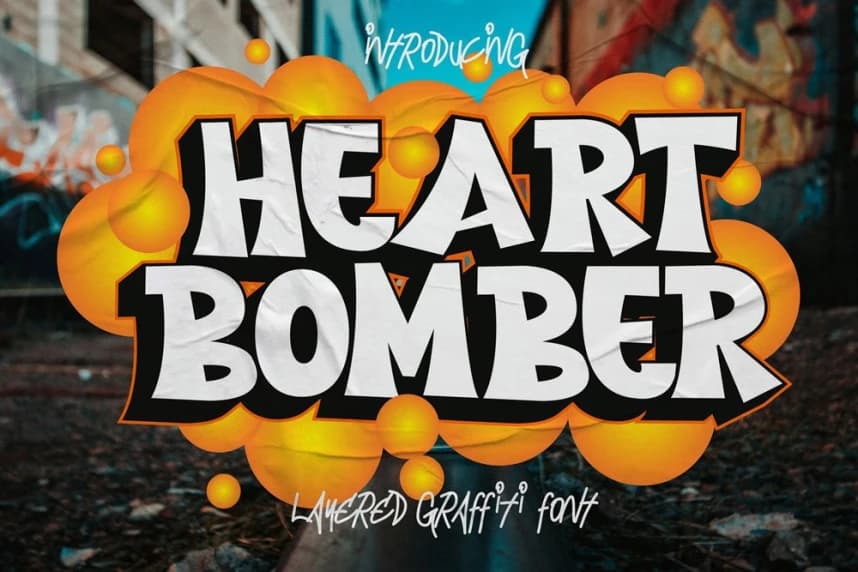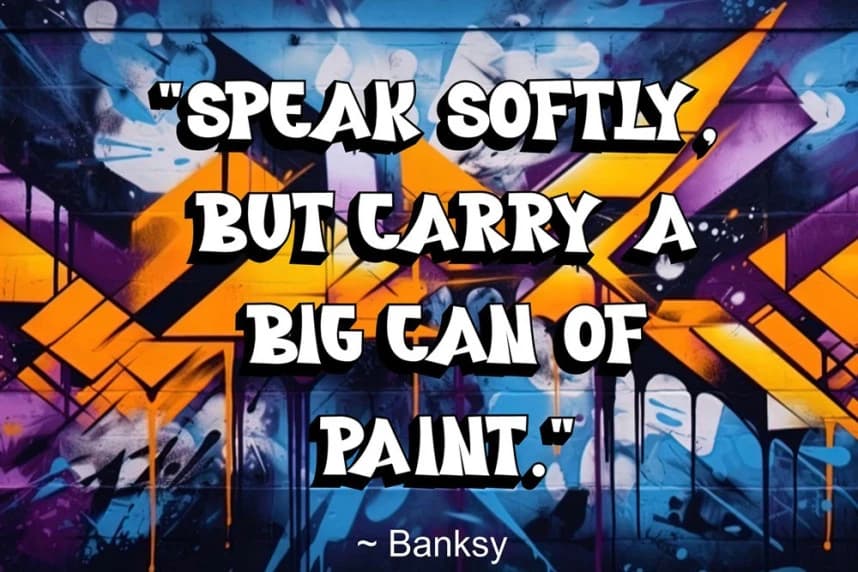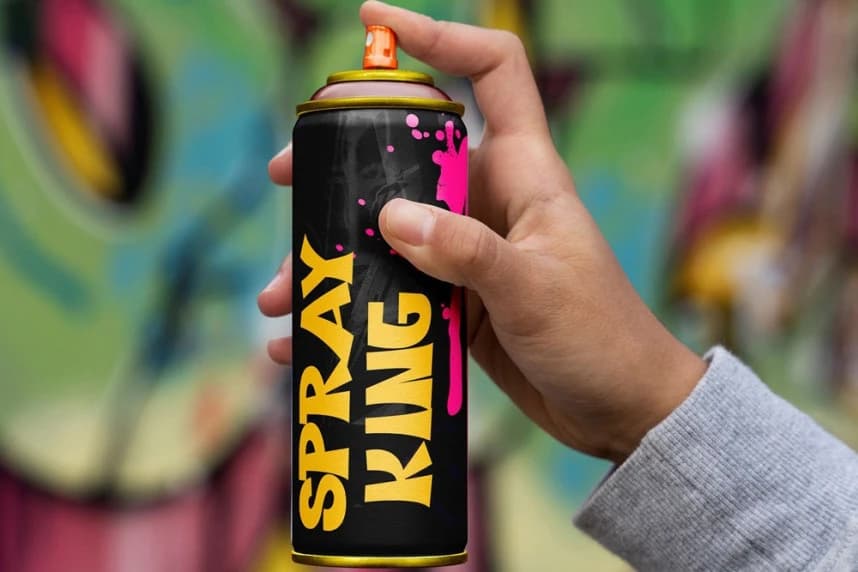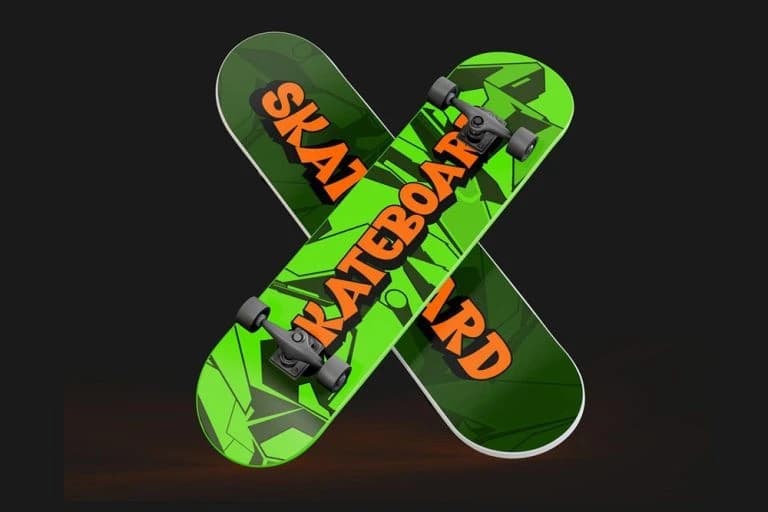
Heart Bomber Font
Heart Bomber Font, cesur ve ifade gücü yüksek bir graffiti fontudur ve kentsel sokak kültürünün ham nabzını yakalar. Öne çıkmak isteyen yaratıcılar için tasarlanan bu gölgeli graffiti fontu, enerjik yazı karakterlerini güçlü bir gölge katmanı ile birleştirerek derinlik katar.
Heart Bomber Font, cesur ve ifade gücü yüksek bir graffiti yazı tipidir ve kentsel sokak kültürünün ham nabzını yakalar. Öne çıkmak isteyen yaratıcılar için tasarlandı; bu gölge graffiti yazı tipi, enerjik harfleri güçlü bir gölge katmanıyla birleştirerek derinlik katar.